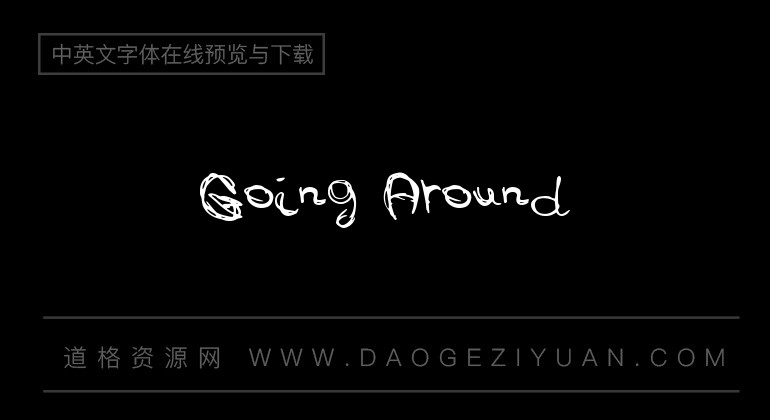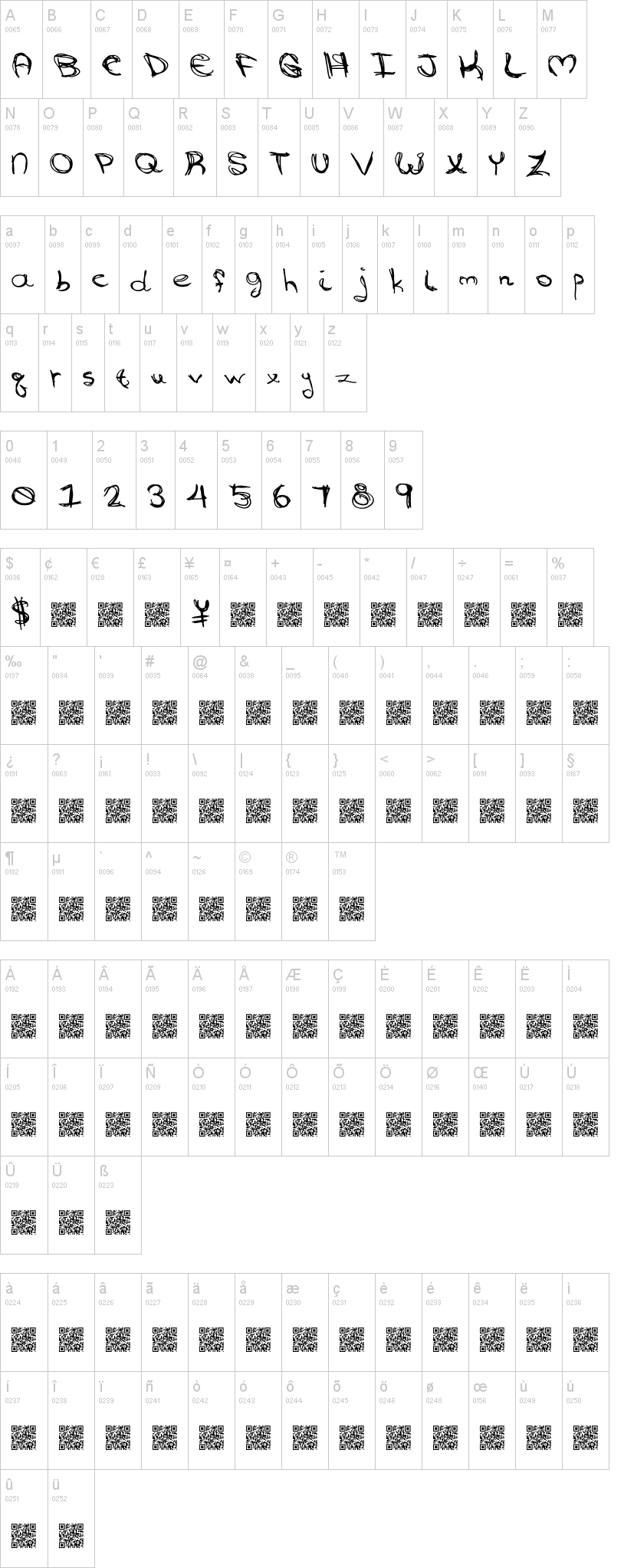
Going Around
Going Around 是一种现代、手写风格的字体,具有非常自然、随意的笔画特色。它是由设计师 Måns Grebäck 开发的,可在多种设计项目中使用。 Going Around 的特点包括: 1. 独特的笔画:该字体的笔画非常自然,仿佛是手写而成。它的笔触非常流畅,较为纤细,这使得该字体非常适合在各种设计中使用,尤其是需要显示出一种随意、非正式的氛围时。 2. 多种字形:Going Around 提供了多种不同的字形,包括正常、粗体、斜体等,这使得你可以在不同的设计中使用不同的字形,以达到更好的效果。 3. 多语言支持:该字体支持许多不同的语言,包括英语、西班牙语、法语、德语等等。这使得该字体在全球范围内得到了广泛的应用。 总的来说,Going Around 是一种非常适合在各种设计项目中使用的字体,它的自然、流畅的笔画和多种字形、多语言支持等特点,使得它在设计师中越来越受欢迎。
Going Around是一款非常不错的手写艺术字体,具有很好的视觉感,适合于文化类的宣传设计、商业类品牌的广告和产品包装设计以及个性化文字排版等较多场景。